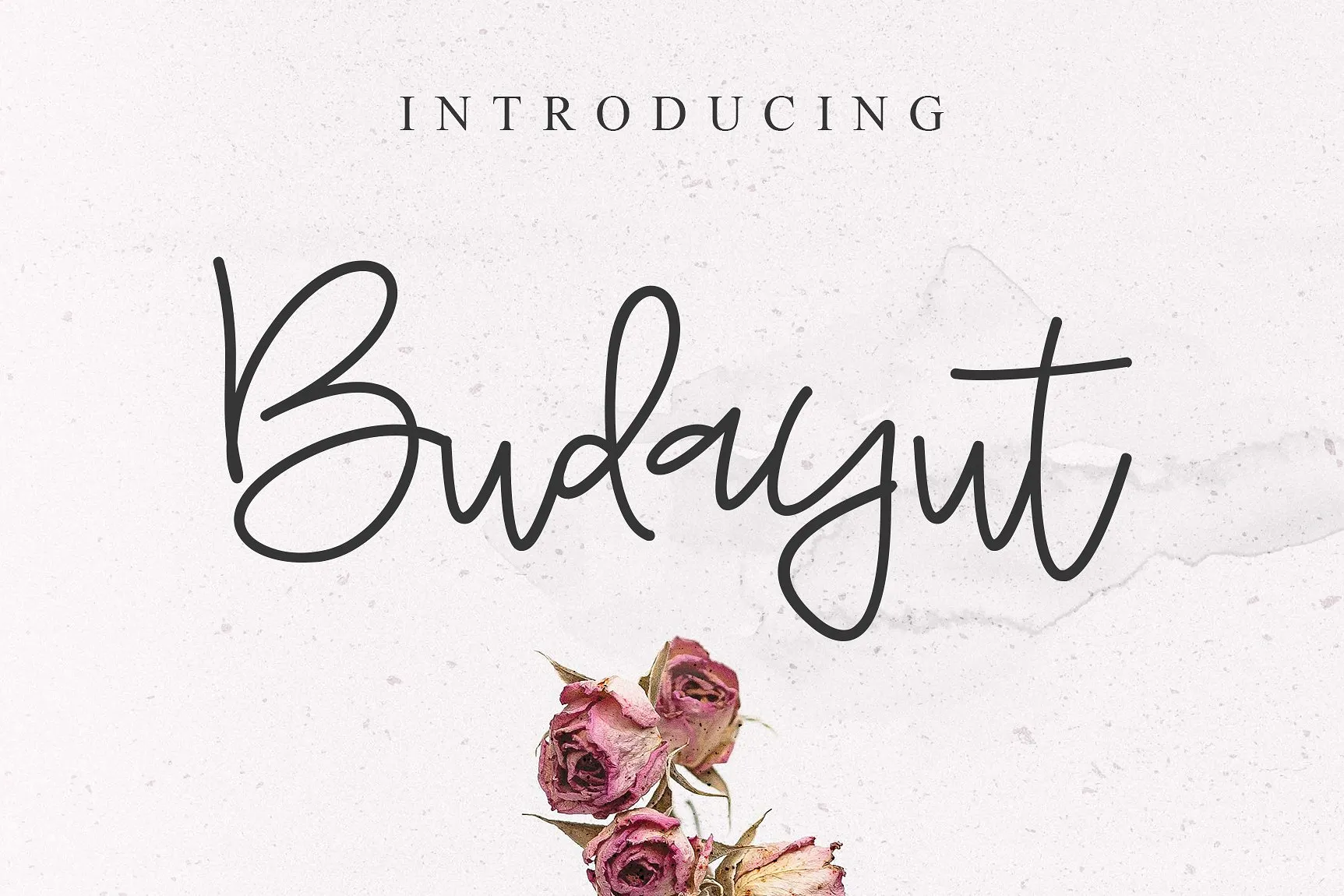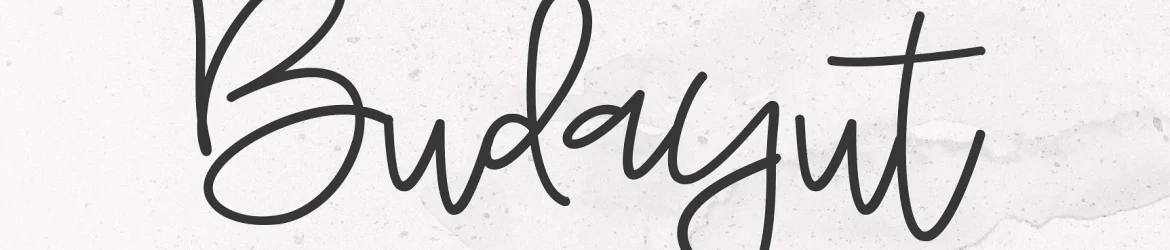
Budayut Signature Font – Download Grátis
Olá! Este é o Budayut Font Signature, uma fonte escrita a mão que foi criada para pessoas que desejam adicionar um toque único e natural aos seus projetos de design. Idealmente desenvolvida como uma ferramenta fácil e versátil para uso em diversos contextos do design, como logotipos, mensagens pessoais, embalagens de produtos, materiais publicitários e até mesmo cartões de agradecimento. Se você é um designer gráfico ou artesanal que busca expressar sua personalidade através dos projetos, esta fonte é perfeitamente adaptada. Com uma aparência natural e suave, o Budayut Font Signature pode ser usada em praticamente todos os tipos de projeto visual. Não importa se você está criando um logotipo para sua empresa, estilizando um texto personalizado ou designando uma embalagem de produto – este é definitivamente aquele elemento que dá seu trabalho a cara única e especializada. O Budayut Font Signature é perfeito para aqueles que querem tornar suas criações mais pessoais e autênticas. É fácil de usar, fácil de manusear e oferece um resultado natural e sofisticado que combina harmoniosamente com qualquer design. Essa fonte não apenas aprimora sua capacidade como designer, mas também é uma maneira para você expressar seu estilo único através da escrita e do design. Não perca tempo – comece criando hoje!